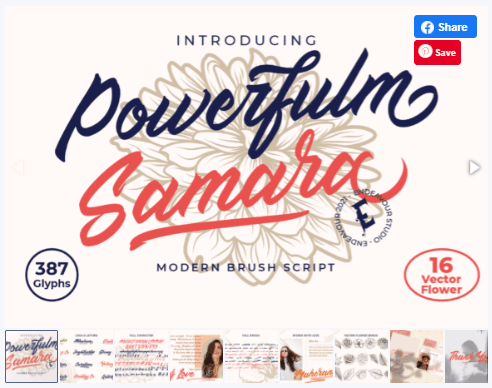
Powerfulm Samara Font
Powerfulm Samara - классический скриптовый шрифт. Его естественный и уникальный стиль делает его невероятно подходящим для большого количества дизайнов. Единственным ограничением является ваше воображение! Этот шрифт имеет кодировку PUA, что означает, что вы можете легко получить доступ ко всем глифам и росчеркам!